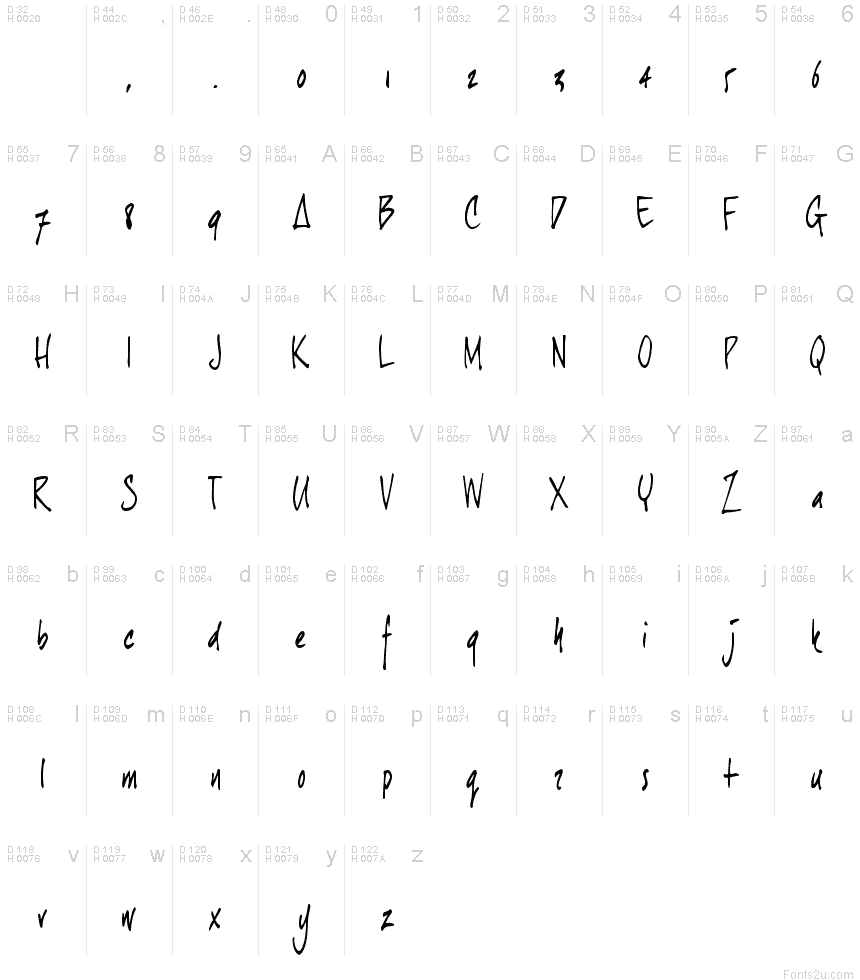
joeHand 1 字体
joeHand 字体家族,包含 4 款字体
joeHand 1
joeHand 1 (由 J O E B O B graphics 设计) 是一款免费的手写字体,带有随性的节奏感,就像用马克笔快速书写的一样。其笔画不均,时而呈现纤细的直笔,时而化为厚重的墨迹曲线;不规则的连笔和活泼的字形让字体充满了个人色彩,而非刻意的精雕细琢。
这款免费字体非常适合用于海报、杂志封面、专辑封面、咖啡馆菜单以及手工制品标签等需要展现非正式、人性化质感的场合。它也非常适合短标题和主题卡片,其舒展的字形和强烈的笔触变化,仅仅通过几个字就能传递出充沛的活力。